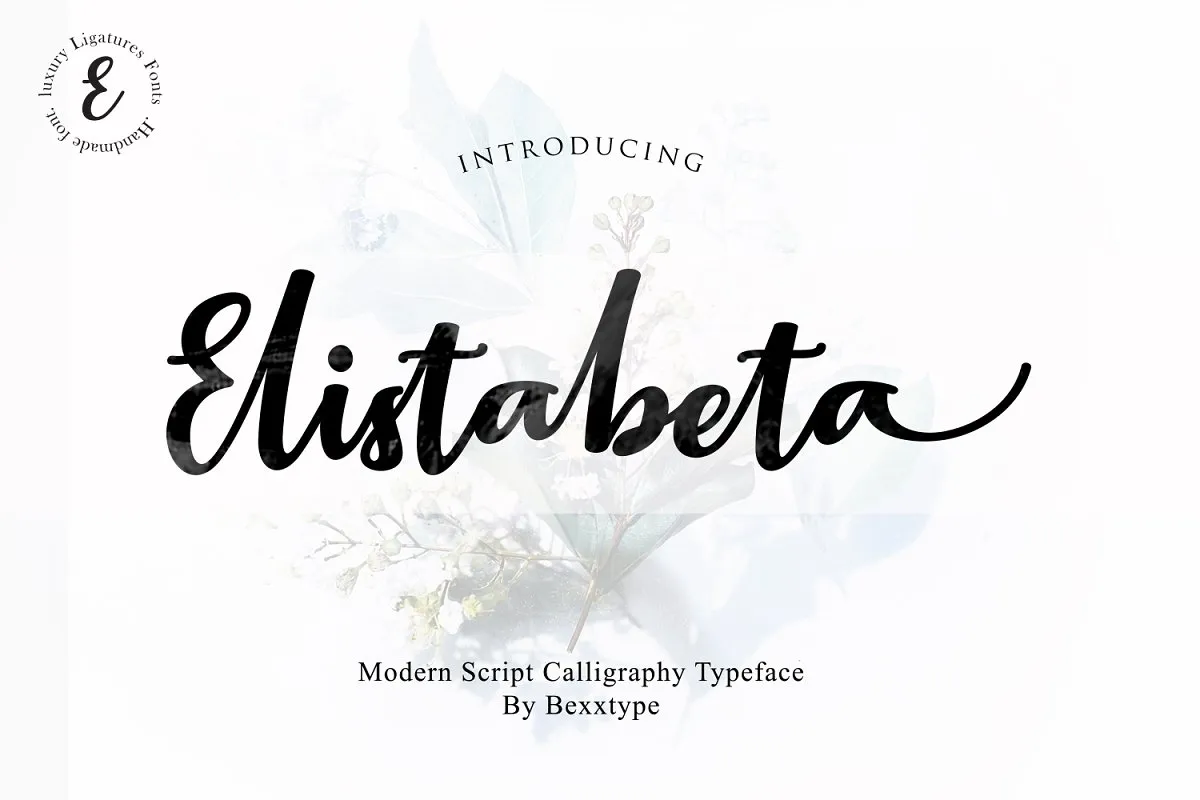
Descubra a modernidade sofisticada da Elistabeta Font, uma tipografia script moderna criada pela Bexxtype. Elistabeta é uma mistura única e vibrante de estilo calligrafia manuscrita, com seus caracteres decorativos que parecem dançar ao longo do texto. Esta fonte traz a elegância da script gráfica contemporânea para seu próximo projeto – seja ele um convite de casamento, cartão de boas-vindas, material de marca, cartões de negócios ou até mesmo uma impressão publicitária em outdoors. Com Elistabeta, você pode criar design visualmente atraente e único que destaca seu trabalho. Suas linhas fluidas, desenhos decorativos e estilo calligrafia manuscrita garantem que seu projeto ganhe notoriedade e seja memorável. Seja para uma publicidade de alto impacto ou simplesmente um cartão personalizado, Elistabeta está sempre pronto para dar vida a seus ideais visuais. Descubra agora como esta fonte pode transformar sua próxima criação em algo excepcional.